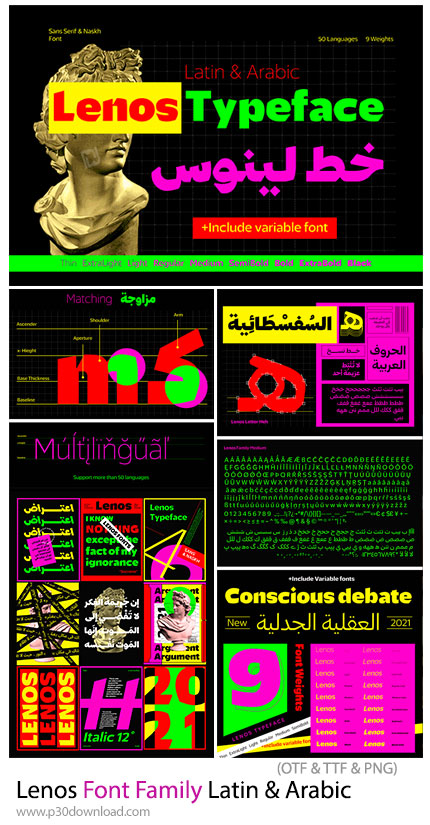
لنوس (Lenos) نسخه مدرنی از فونت عربی قدیمی "نسخ" است، یک فونت ارگانیک مدرن که سنس و "نسخ" را در یک خانواده قدرتمند با 9 وزن مختلف از نازک تا سیاه و تمام گزینههای مورب آن ترکیب میکند. لنوس بیش از 50 زبان مختلف را از جمله اردو، فارسی، اسپانیایی، ترکی و غیره، ترکیب میکند و همگی قابل استفاده در برنامههای دیجیتال و آفلاین هستند. این فونت زیبا با فرمت های OTF و TTF و PNG بر روی سایت برای دانلود قرار گرفته است.